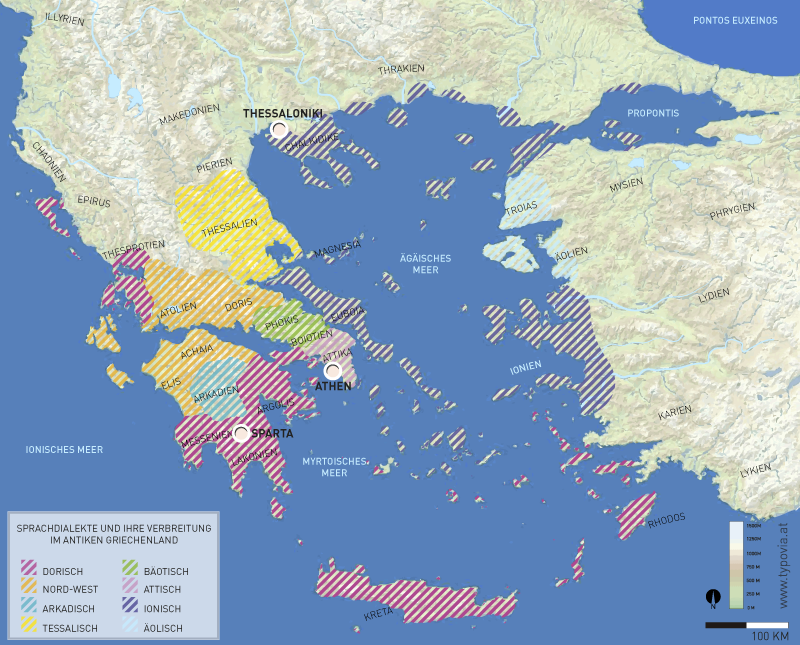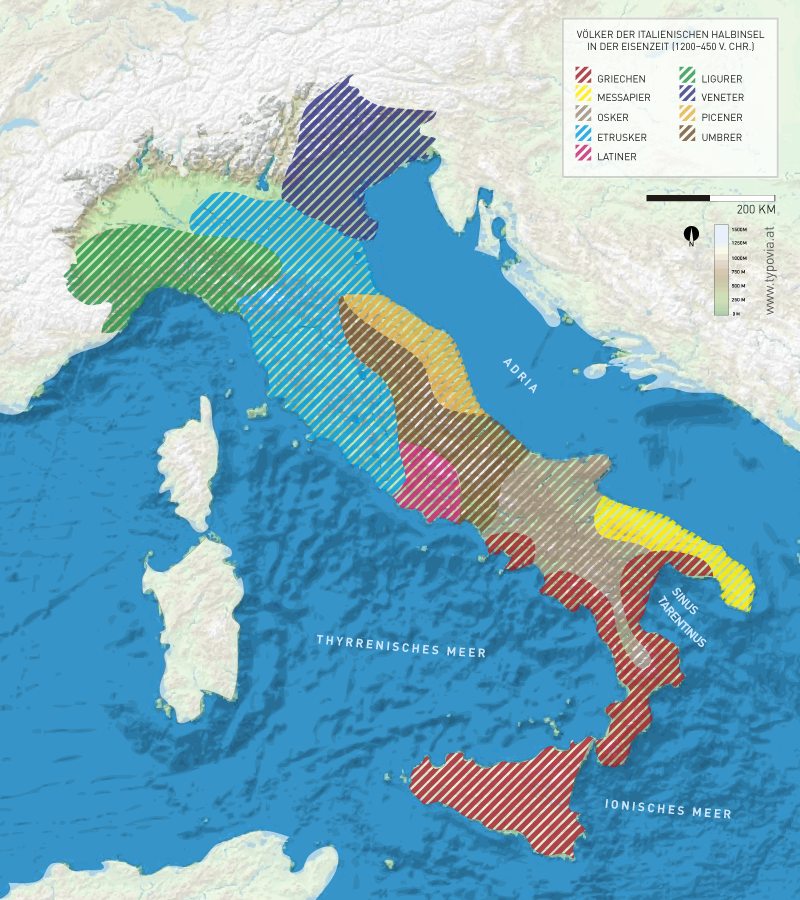
II. Phönizien, Griechenland und antikes Rom
An der östlichen Mittelmeerküste siedelte sich im 2. Jahrtausend v. Chr. ein Seefahrervolk an, das von Homer als „Phönizier“ 17 bezeichnet wurde. Die Phönizier selbst bezeichneten sich nach den Namen der Städte, aus denen sie kamen. Sie entwickelten ein dichtes Städtenetz entlang der Küste der Mittelmeeres, das einen blühenden Handel ermöglichte. Den Höhepunkt der Entwicklung erlebte Phönizien in den Jahren 1000–600 v. Chr. Nach der Belagerung von Tyros durch das Heer des babylonischen Königs Nebukadnezar II. im Jahr 573 v. Chr., wird ganz Phönizien etwa 40 Jahre später Teil des persischen Reiches. Die Städte werden nach und nach zerstört; nach dem Tod Alexander des Großen im Jahr 323 v. Chr. verliert Phönizien gänzlich an Bedeutung.Das Volk hat eine semitische Sprache gesprochen und entwickelte aus dem Protokaanäischen um 1100 v.Chr. ein Schriftsystem, das als Vorläufer des griechischen, hebräischen und arabischen Alphabets gesehen werden kann. Die Namen der 22 Zeichen tragen semitische Bezeichnungen. Diese (ab 800 v. Chr.) rechtsläufige Schrift, die nur Konsonanten und keine Vokale hatte, verbreitete sich im gesamten Mittelmeerraum. Wie und ob sich die Linearschrift A – die auf Kreta entstand und nicht-griechisch war – und das phönizische Alphabet gegenseitig beeinflusst haben, ist nach wie vor Gegenstand der Forschung. Die frühesten bekannten Inschriften des phönizischen Alphabets stammen aus Byblos und sind um das Jahr 1000 v. Chr. entstanden.
Einen Zwischenschritt zur Entstehung des griechischen Alphabets bildet die Linearschrift B. Sie gilt als die Silbenschrift der Mykener und wurde vom 15.–12. Jh. v. Chr. ausgehend von Knossos und Khania auf Kreta und dem griechischen Festland (Pylos, Chania, Mykene, Tiryns und Theben) verwendet. Die Entzifferung dieser Schrift erfolgte spät. Erst im Jahr 1953 schrieb Michael Ventris – dem nach den Vorbereitungsarbeiten von Arthur Evans und später Alice Kober der Durchbruch gelang – seinem Griechisch-Lehrer: „leider nicht ganz das Griechisch, das Sie mir beibrachten! Mit besten Wünschen, Michael“. 18 |
Die Entstehung des griechischen Alphabets kann aufgrund der vorhandenen Funde nicht auf ein bestimmtes Datum festgelegt werden. Einige Anhaltspunkte geben Spielraum für Spekulationen und Thesen:
Die Entwicklung der griechischen Sprache umfasst drei Epochen:
Aus dem Ursemitischen entwickelten sich also im Lauf der Jahre die phönizische, die hebräische, die arabische und die aramäische Schrift. Später, irgendwann zwischen 1200–800 v. Chr., übernahmen die Griechen das Konsonantensystem der Phönizier. Der große Verdienst der Griechen war die Ergänzung des Alphabets mit Vokalen, die als gleichwertige Zeichen notiert wurden. Jene Zeichen des Semitischen, für die es keine Entsprechung im Griechischen gab, wurden zu Vokalen umfunktioniert. Bis zum Jahr 900 n. Chr. war das griechische Alphabet ein Majuskelalphabet. |
Griechenland expandiert ab etwa 800 v. Chr. im gesamten Mittelmeergebiet. Als Gründe dafür werden sowohl Rohstoff- und Nahrungsmittelknappheit als auch Gruppeneinflüsse und -kämpfe vermutet. Den Emigranten – unter der Leitung der Expeditionsspezialisten (οἰκιστής ‚Oikistes‘) – wurden Vorräte und Mittel für die Gründung einer neuen Kolonie zur Verfügung gestellt. Die Griechen siedeln sich vorwiegend am unterem Rand der italienischen Halbinsel und auf Sizilien an. Die Kolonien und ihre Einwohner sind so zahlreich, dass dieses Gebiet die Bezeichnung „Magna Græcia“ (Μεγάλη ῾Ελλάς ‚Megale Hellas‘ = Großgriechenland) erhält. Die Griechen bringen auf die Halbinsel nicht nur ihr relativ neues Alphabet, sondern auch ihre fortgeschrittene Kultur (darunter die Werke Homers, die wahrscheinlich in den Jahren 850–750 v. Chr. enstanden sind). Das archaisches Italien ist von verschiedenen Völkern besiedelt, von denen die Etrusker und Latiner am weitesten entwickelt waren. Die Schrift der Griechen, die die hebräischen Alphabetzeichen in ihr Zeichensystem übernommen haben, diente wiederum den Latinern – neben der etruskischen Schrift – bei der Formung der lateinischen Buchstaben. Die Zeichen G, J, U, W und Y wurden ursprünglich nicht benötigt. 19 Die Lateinische Sprache, die als Frühlatein von den Latinern seit dem 8 Jh. v. Chr. gesprochen wurde, entwickelte sich im Imperium Romanum zur Amtssprache (klassisches Latein). Zum Zeitpunkt der größten Ausdehnung des Römischen Reiches im Jahr 117 n. Chr. unter Kaiser Trajan ist Latein die Muttersprache der ansässigen Bevölkerung. Die Zeichen des lateinischen Alphabets bestehen vorerst nur aus Großbuchstaben (Majuskelalphabet). Im antiken Rom entwickeln sich folgende Formen des „Abecedariums“:
Die Herrschaft der Römer über die Völker des Mittelmeeres trug zur Verbreitung der lateinischen Sprache bei. Die Erhebung des christlichen Glaubens zur Staatsreligion des Imperiums (391 n. Chr.) und die spätere Missionierungstätigkeit der römischen Kirche waren Anlass für die Etablierung von Latein als universelle Sprache. Diese war jedoch abermals den herrschenden Schichten vorbehalten, während das einfache Volk sich der Landessprache bediente bzw. der Schreibkunst gar nicht mächtig war („biblia pauperum“ 20). Die Verbreitung des römisch-katholischen Glaubens brachte auch die Verbreitung der Schrift mit sich – sei es in Form von Manuskripten der Bibel, von staatlichen Urkunden, von päpstlichen Bullen usw. In Gelehrtenkreisen errang Griechisch große Bedeutung. Die großen Theologen und Exegeten des Mittelalters bauten ihre Theorien nicht selten auf dem Gedankengut der griechischen Philosophie, Logik, Ethik etc. auf. Während die Gebildeten Lateinisch bzw. Griechisch sprachen und schrieben, war die Volkssprache die Sprache der „Heiden“. Die Ausbreitung, der Einfluss und die Bekanntheit der semitischen Sprache in den ersten Jahrhunderten n. Chr. hing damit zusammen, dass die Christen die heiligen Schriften des Volkes Israel als das „Alte Testament“ in ihren Kanon aufgenommen hatten. Zahlreiche Übersetzungen dieser Schriften ins Griechische halfen, dass die Sprache nicht in Vergessenheit geriet. Bis heute existiert das s. g. Althebräisch, die Sprache der Bibel, neben dem modernen Hebrit. Bedeutende Rolle spielt im Judentum der Talmud, die Diskussion der Mischna und Gemara. Der Talmud besteht aus der mündlichen Überlieferung und Auslegung der Zehn Gebote (die Moses auf dem Berg Sinai erhielt), aber auch aus der Sammlung von Gesetzen, Geschichten, Gleichnissen und Erzählungen pädagogisch-ethischen Charakters. Auch die Kabbalah, eine Richtung im jüdischen Mystizismus, erfreute sich in prädestinierten Kreisen großer Beliebtheit. Die Teilung des Imperium Romanum in das westliche und östliche Reich (nach dem Tod des Kaisers Theodosius 395 n. Chr.) und der damit eingeleitete Zerfall des Kaisertums sowie die beginnenden Völkerwanderungen verwandeln Europa in einen „Rangierbahnhof“ der Sprachen, Dialekte und Alphabete. Europa befindet sich in der staatsbildenden Phase, die noch Jahrhunderte andauert … |
17 Φοίνιϰες ‚Phoinikes‘ = Purpurhändler; den Farbstoff haben die Phönizier aus der Purpurschnecke gewonnen – aus 12.000 Schnecken ließen sich 1,5 Gramm des Farbstoffes gewinnen; für ein Kilogramm Wolle wurden 200 Gramm Farbstoff benötigt, das sind drei Kilogramm Drüsensaft.
18 Nach: Robinson A., Die Geschichte der Schrift, Albatros Verlag, Düsseldorf: 2004, S. 119.
19 Der Konsolidierungsprozess des lateinischen Alphabets endet erst im lateinischen Mittelalter. Das Alphabet zählte danach 23 Buchstaben. Die Theologen sahen im kirchlichen Latein die Vollendung der beiden Testamente: des Alten (Hebräisch hat 22 Glyphen) und des Neuen (Griechisch hat 24 Glyphen). Im modernen lateinischen Alphabet sind die Zeichen J, U und W hinzugekommen.
20 ‚Biblia pauperum‘ = ‚Bibel der Armen‘ bezeichnet die Erzählungen der biblischen Geschichten in Bildern; die biblischen Motive finden sich auf zahlreichen Fresken, Bildern und Altären in den Kirchenräumen der ausgehenden Antike und des Mittelalters.
Der Einfluss des Semitischen auf die Bildung des phönizischen und griechischen Alphabetes: